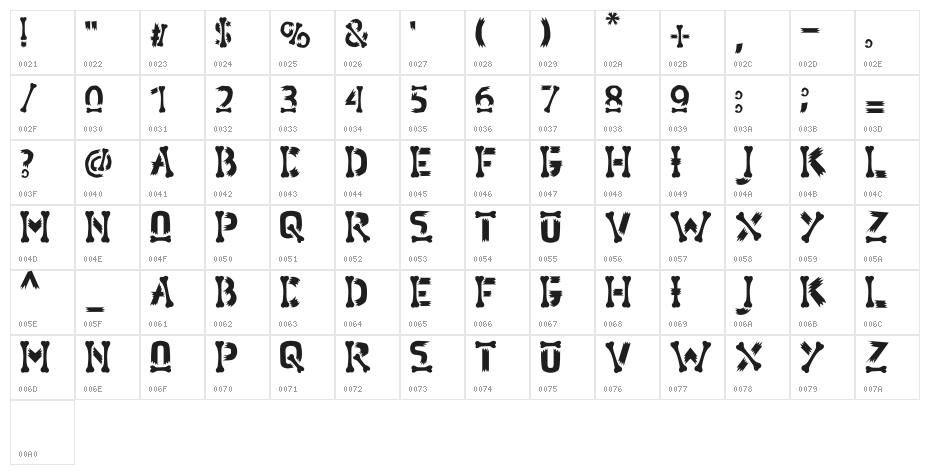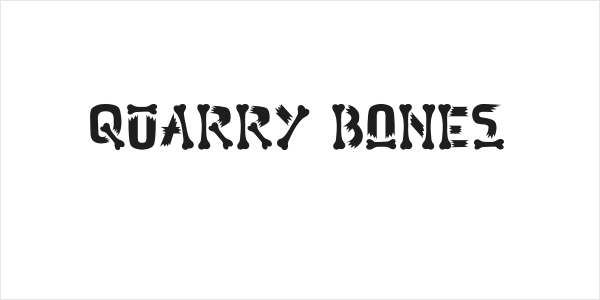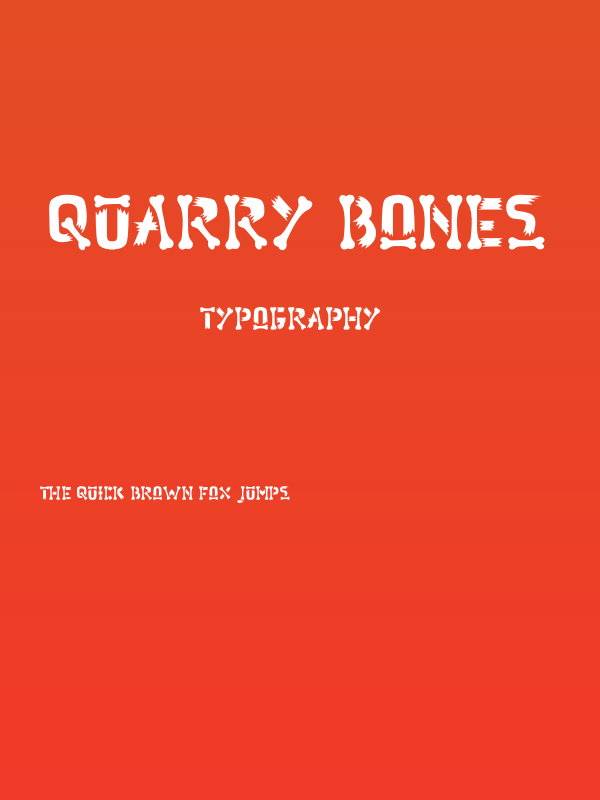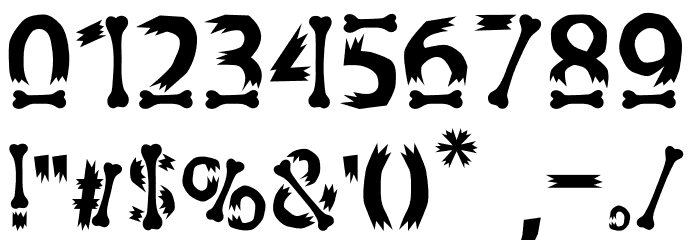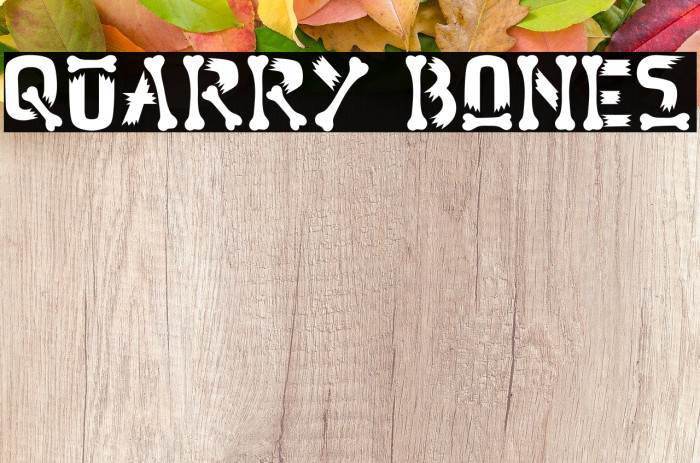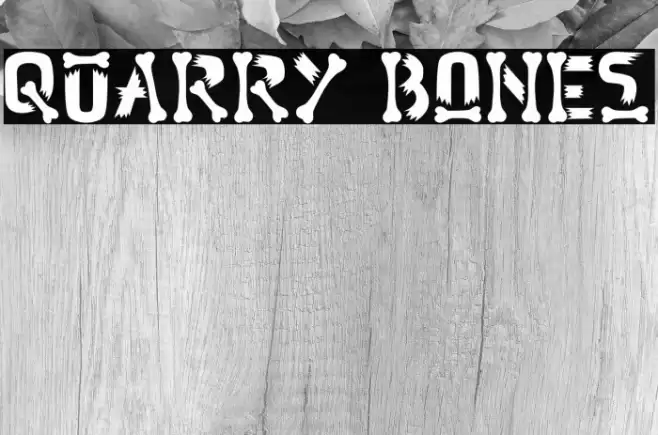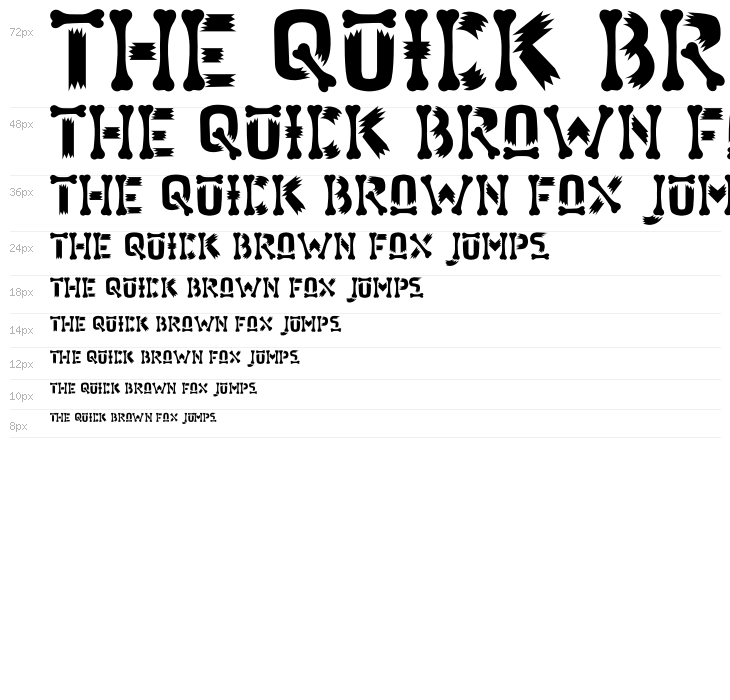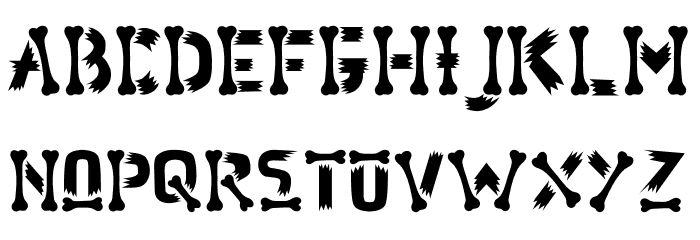
Quarry Bones Font
| Рекомендуемые проекты | Perfect for Halloween posters, horror movie titles, themed party invitations, and edgy graphic designs. |